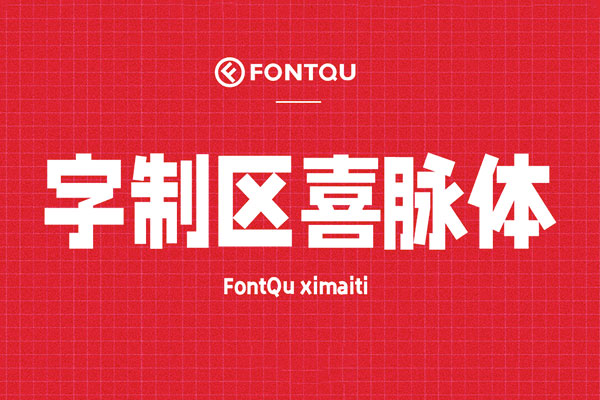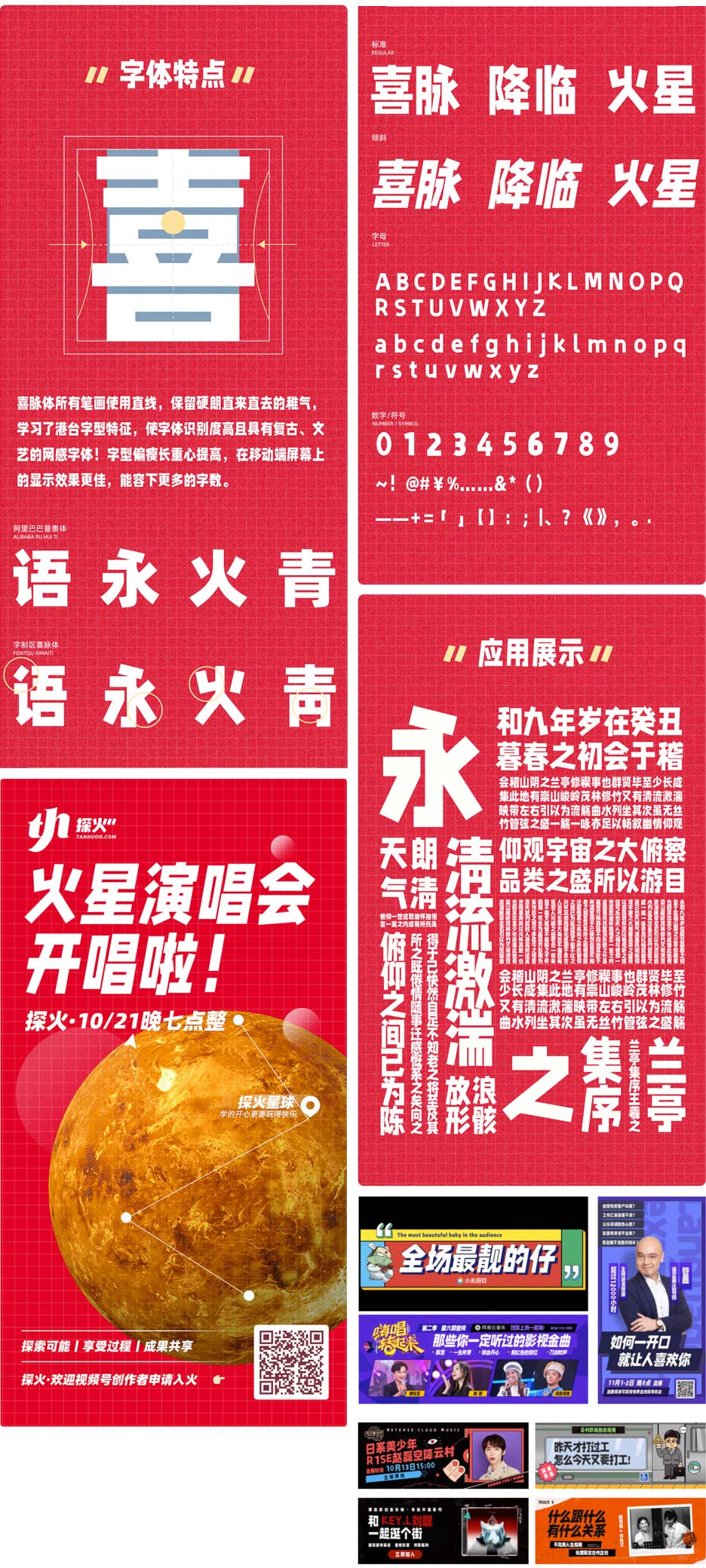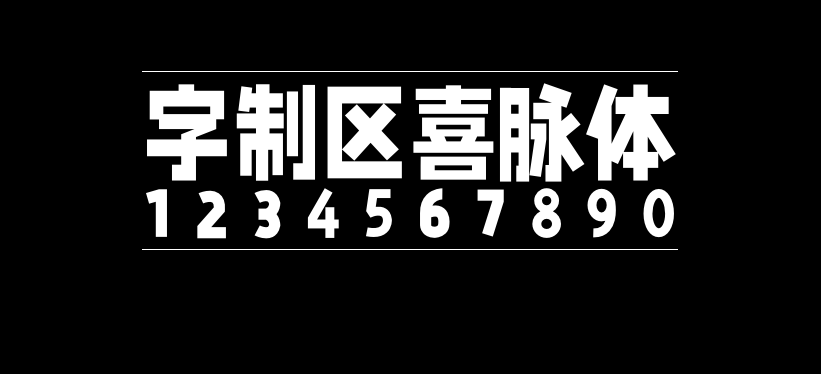
字制区喜脉体
字制区喜脉体是字制区(FONTQU)发布的首款免费商业字体,对外发布于2021年1月1日凌晨0点,祝大家新年快乐!
我国在5G技术、短视频行业上遥遥领先远胜他国,在这快速发展的节骨眼上,字体文化的发展却没能跟上,创作者永远缺少-款合适手机屏幕的免费字体、缺少一款具有网感的免费综艺字体;所以我们想尽一点力,给咱们即将到来的30岁留下-点热血与喜爱!于是诞生了这款–字制区喜脉体!
字制区喜脉体所有笔画使用直线,保留硬朗直来直去的稚气,学习了港台字型特征,使字体识别度高且具有复古、文艺的网感字体!字型偏瘦长重心提高,在移动端屏幕上的显示效果更佳,能容下更多的字数。